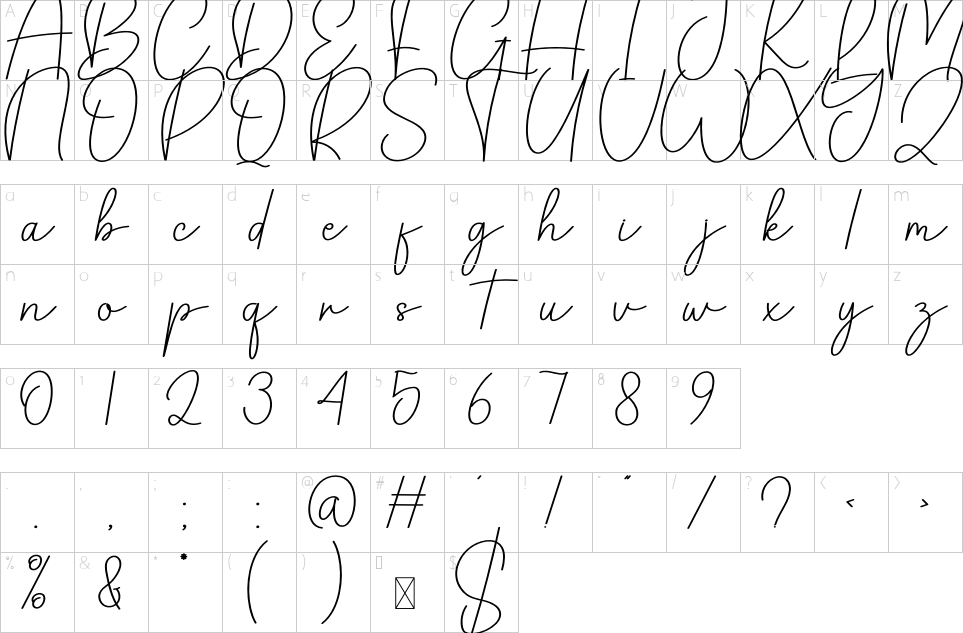
A fonte Pumpkin Signature é um recurso grátis para designers e criativos em todo o Brasil que buscam uma fonte diferente para seus projetos. Desenvolvida por scratchones, esta fonte vem com uma versão para Windows e Mac, adequada para diversos usos. Suas linhas curvas leves e alegres criam uma sensação de vida e alegria, que certamente se adaptam bem para criações como design de logotipos, letras de música e até mesmo para o decoração de sites. Com seu design jovial e criativo, a Pumpkin Signature é uma escolha ótima para quem busca algo que seja único e colorido, sem comprometer a legibilidade. Incluindo uma versão gratuita, não há motivo para não experimentar essa fonte e explorar suas possibilidades.